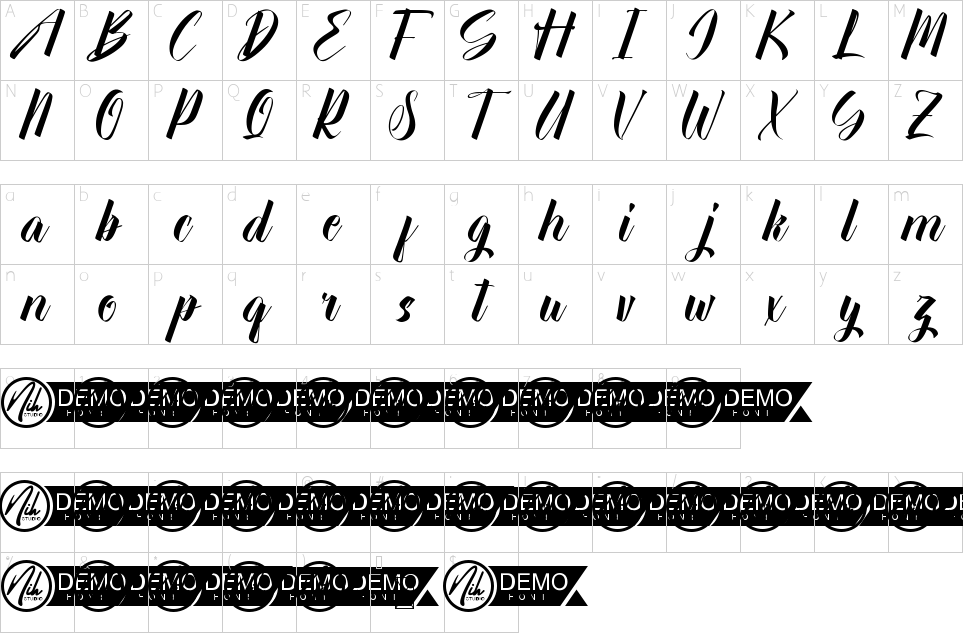
Darling Princess Font – Download Grátis
A Darling Princess Font é uma opção elegante para designers e hobbyistas que procuram uma fonte grata para seus projetos criativos. Desenvolvida pela nihstudio, essa fonte vem como um download limpo para ambientes Windows e Mac, facilitando a integração em qualquer projeto de design digital. Com seu estilo encantador e arredondado, a Darling Princess é perfeita para nomes de aplicativos de beleza ou até mesmo projetos infantis. Sua facilidade de uso e sua versão gratuita oferecem uma excelente opção para aqueles que buscam graciosidade em seus design. Com mais de 1300 downloads desde seu lançamento, é evidente a sua adequação àqueles buscando estilos diferentes sem comprometer a qualidade do projeto.